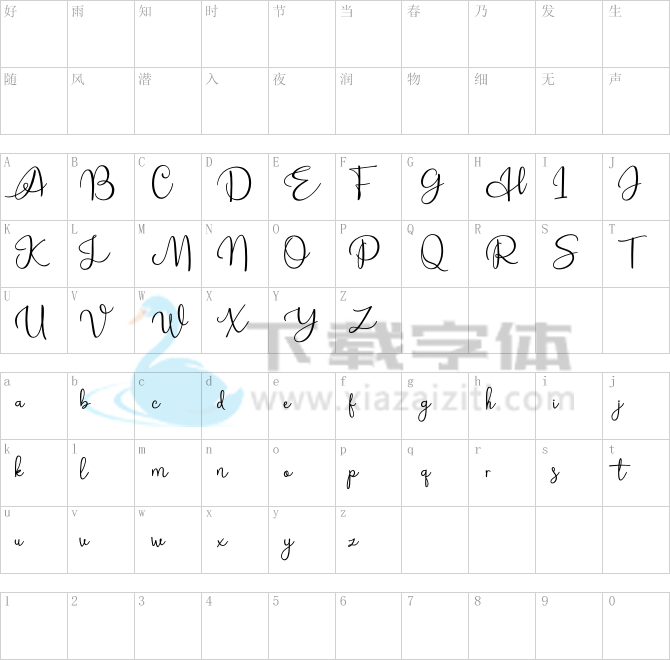
Alleysha.ttf字体下载
Alleysha.ttf字体下载,这款字体结构工整、笔画清晰,兼顾美观与易读性,适用于标题、正文、海报、包装、LOGO 等多种场景。字形优雅稳定,风格百搭耐看,适配日常排版与创意设计,让文字呈现更舒适、更具质感。Alleysha.ttf字体下载一笔一画,皆是细节,以均衡的比例、流畅的线条打造舒适视觉体验,字形端正大气,风格简约现代。无论是商业设计、品牌宣传还是日常排版,都能轻松驾驭,让文字更有格调与力量。Alleysha.ttf字体下载字体下载。